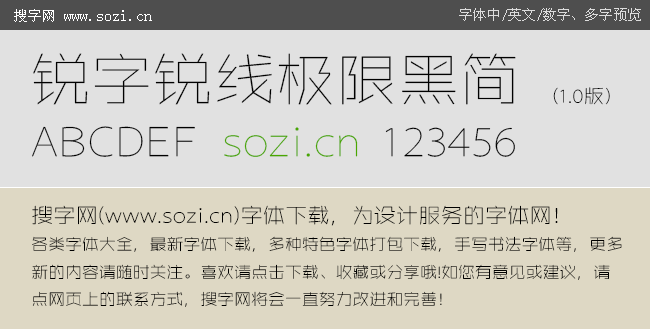
銳字銳線極限黑簡(jiǎn)1.0
搜字網(wǎng)提供一款銳字銳線極限黑簡(jiǎn)1.0中文字體下載,銳字銳線極限黑簡(jiǎn)是一款以線體為原形設(shè)計(jì)的中文藝術(shù)字體,字體簡(jiǎn)潔漂亮,效果非常出色,GBK編碼收字更全,適合應(yīng)用于廣告設(shè)計(jì)、名片設(shè)計(jì)、包裝印刷、產(chǎn)品設(shè)計(jì)等應(yīng)用。